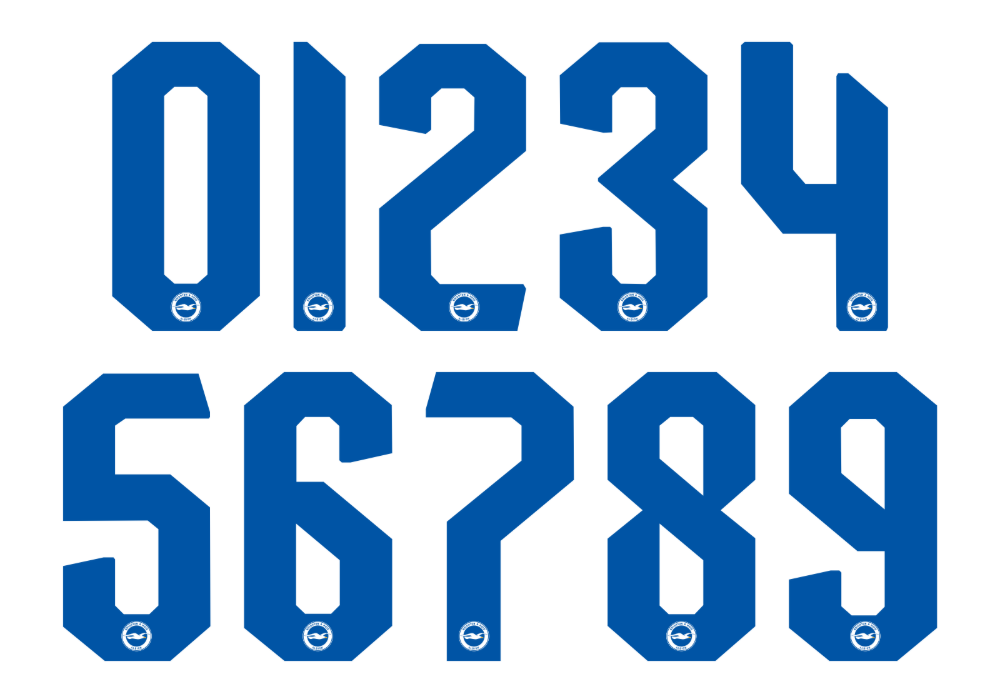
O Brighton & Hove Albion se consolidou como um dos times mais táticos e interessantes de assistir na Premier League. Para a temporada 2025/2026, a parceria com a Nike trouxe uniformes que misturam a identidade clássica das listras com toques futuristas.
Se você é designer, trabalha com sublimação ou apenas quer personalizar a camisa dos Seagulls com fidelidade máxima, disponibilizamos aqui a tipografia oficial utilizada pelo clube em competições de Copas e torneios continentais.
Estilo Visual e Design
A tipografia desenvolvida para o Brighton nesta temporada segue a tendência minimalista e funcional da Nike. É uma fonte sans-serif (sem serifa) com espessura média, projetada para oferecer leitura rápida e clara, mesmo à distância ou em movimento.
Os números possuem cortes internos estratégicos que modernizam o visual sem perder a sobriedade necessária para contrastar tanto com o uniforme titular (azul e branco) quanto com os kits alternativos (geralmente em cores vibrantes como amarelo ou carmesim). É o detalhe que falta para deixar seu projeto com “cara de oficial”.